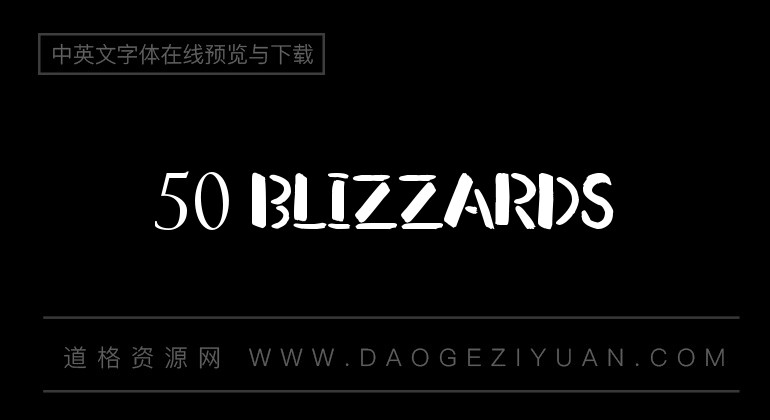
50 Blizzards
? 50 Blizzards 字体是一款拥有令人惊叹的设计风格的字体,它具有古典的外观,但又不失现代感。它的特点是粗体的字母,细节精确、线条流畅,让您的文字更有质感。它还具有更多的多语言支持,可以让您的文字更加精美。
50 Blizzards是一款非常不错的手写艺术字体,具有很好的视觉感,适合于文化类的宣传设计、商业类品牌的广告和产品包装设计以及个性化文字排版等较多场景。